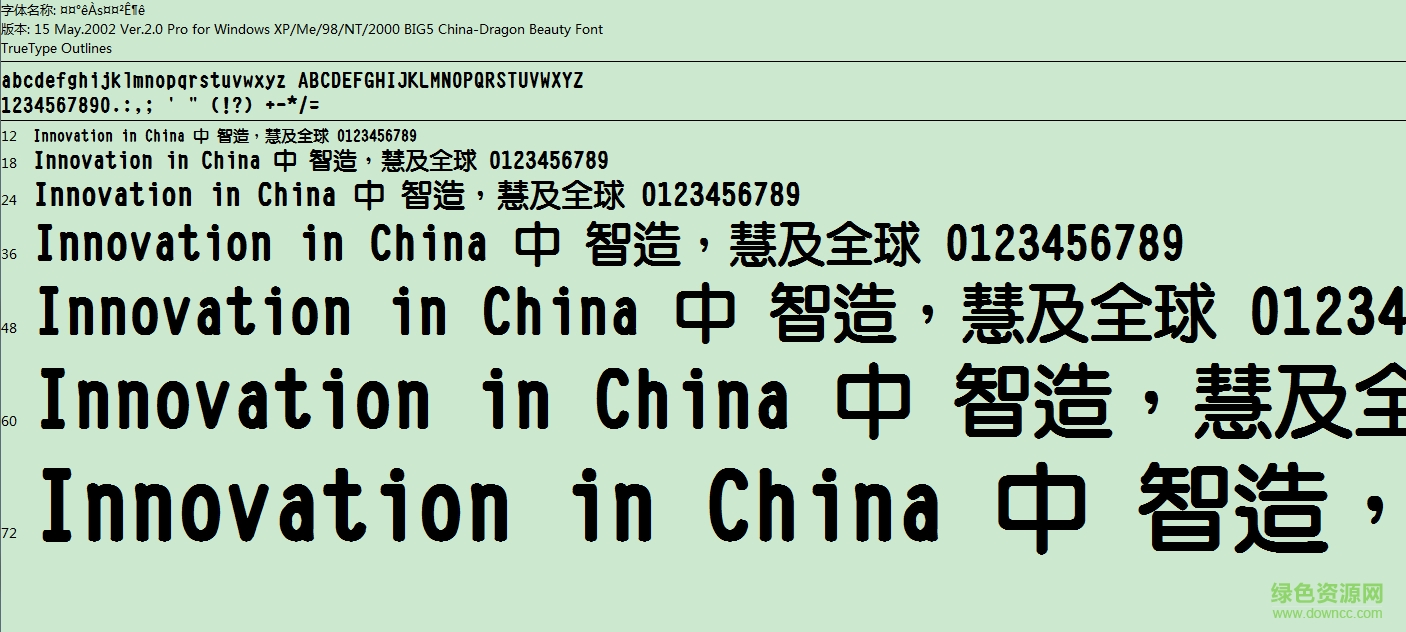
中國龍中粗圓字體大家可以免費(fèi)下載安裝使用!這款字體常被用于印刷設(shè)計(jì)、平面廣告設(shè)計(jì)以及一些簡單的海報(bào)宣傳冊(cè)設(shè)計(jì)等。字體圓潤美觀。歡迎用戶下載使用。
中國龍中粗圓字體遒勁豪放、布局精當(dāng)、結(jié)構(gòu)嚴(yán)謹(jǐn),看上去十分美觀,整體效果非常統(tǒng)一,且字庫完整,可以廣泛應(yīng)用于出版印刷、文學(xué)雜志、宣傳海報(bào)、ppt等等!需要的用快來綠色資源網(wǎng)下載安裝吧。